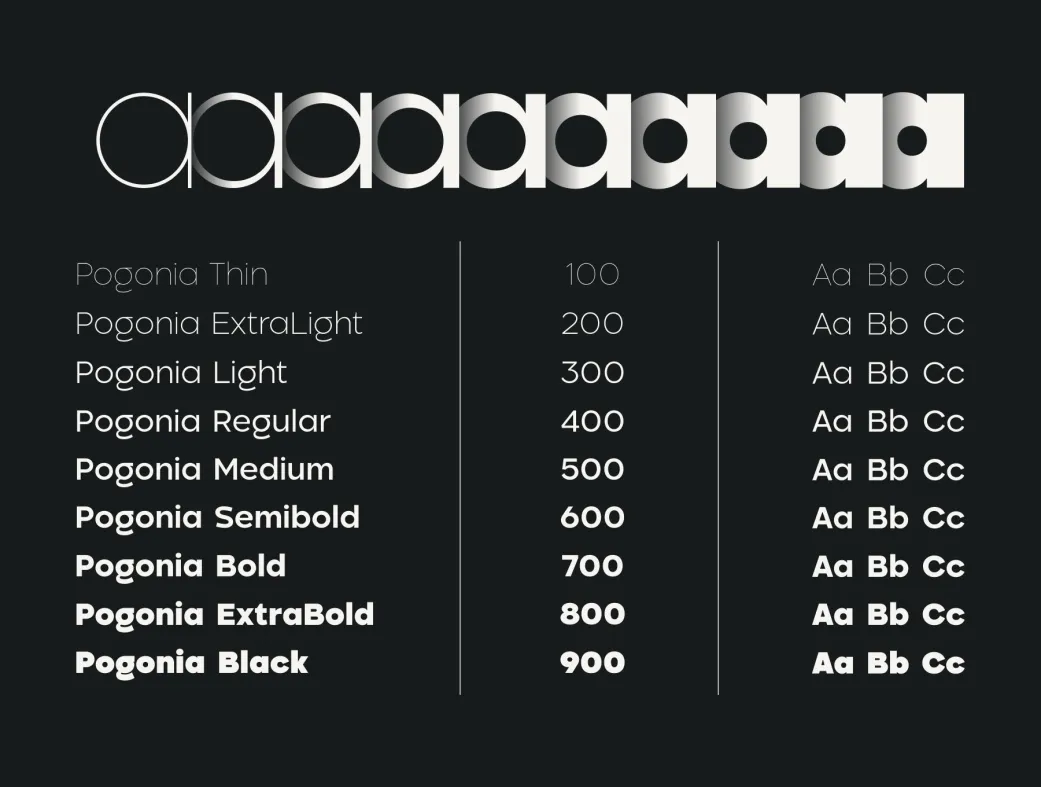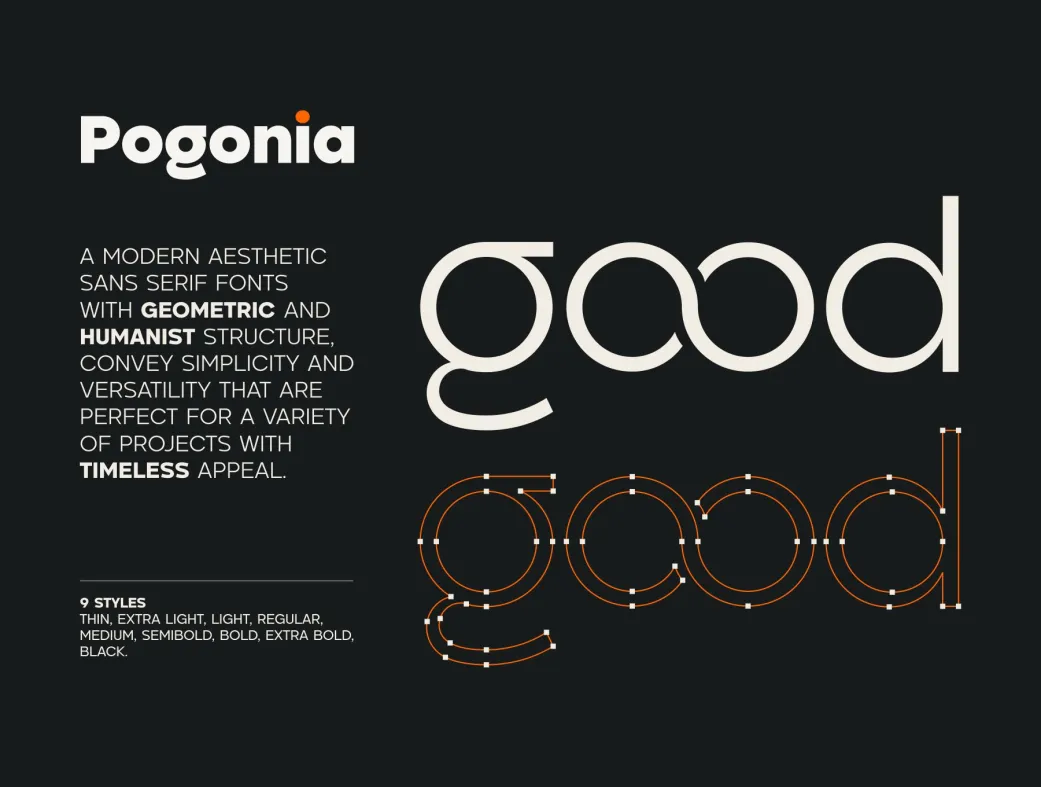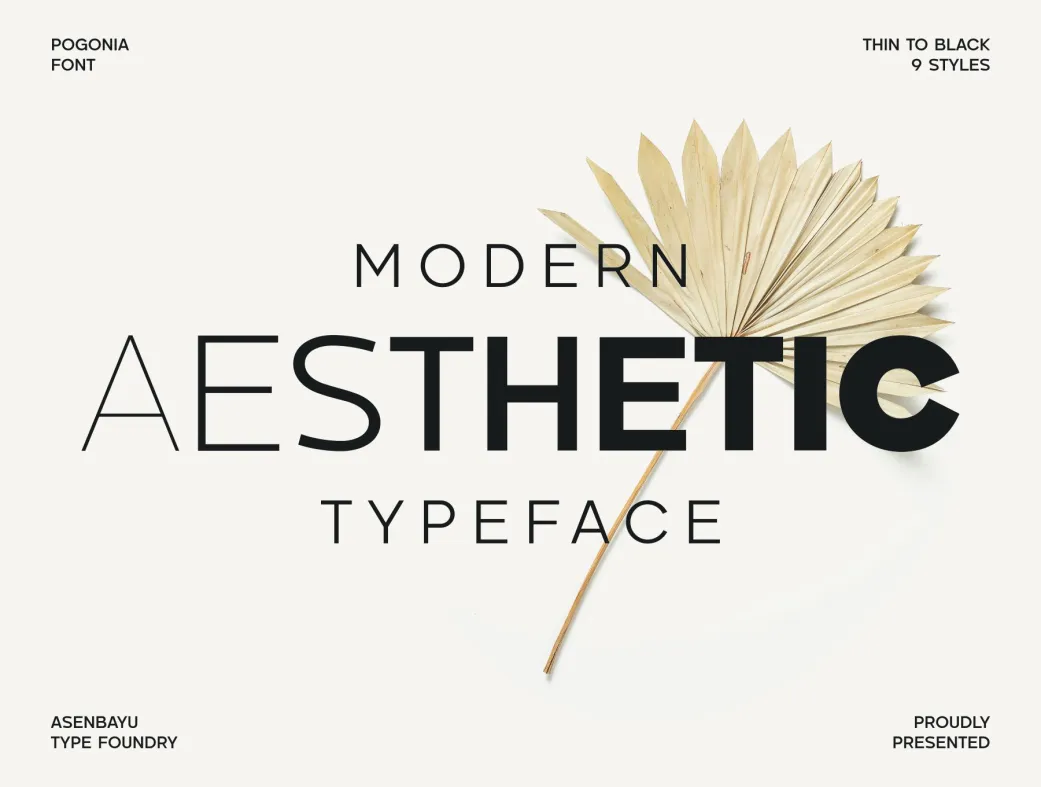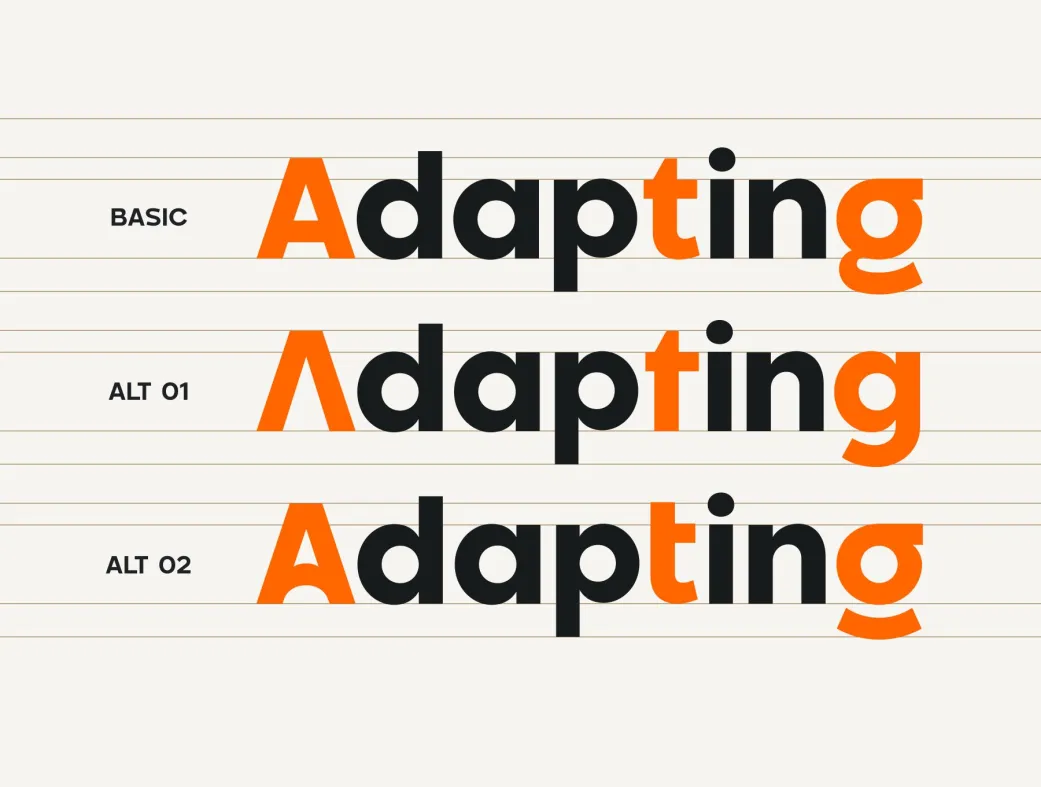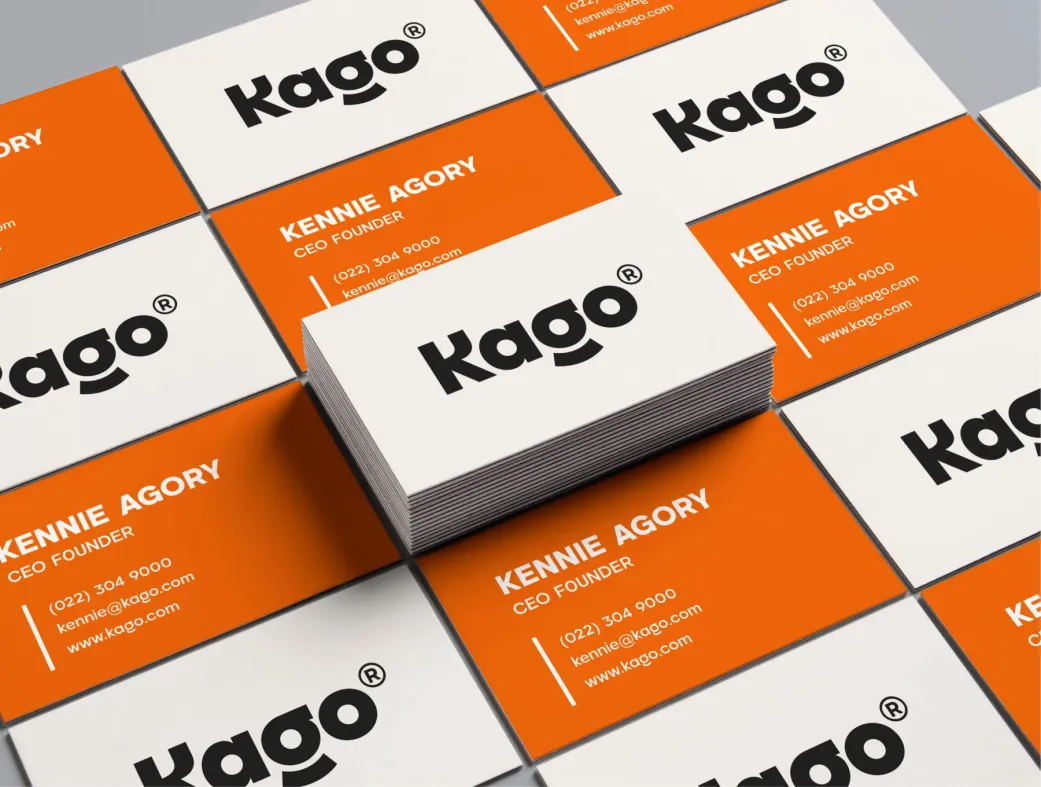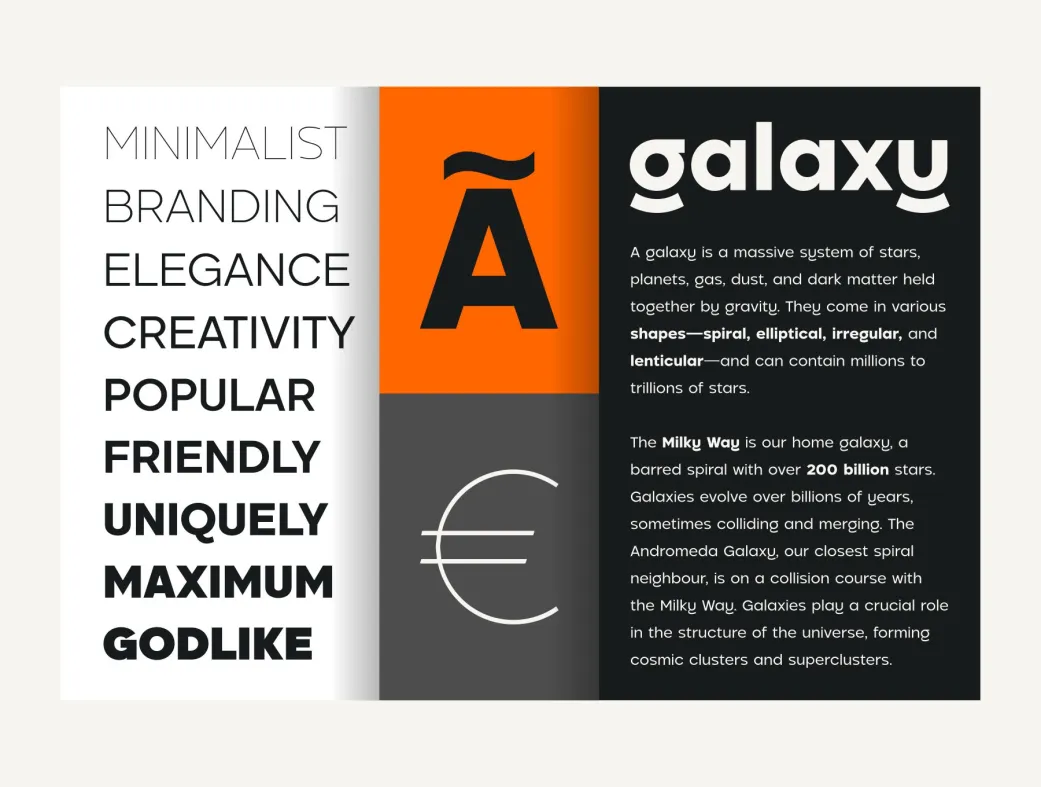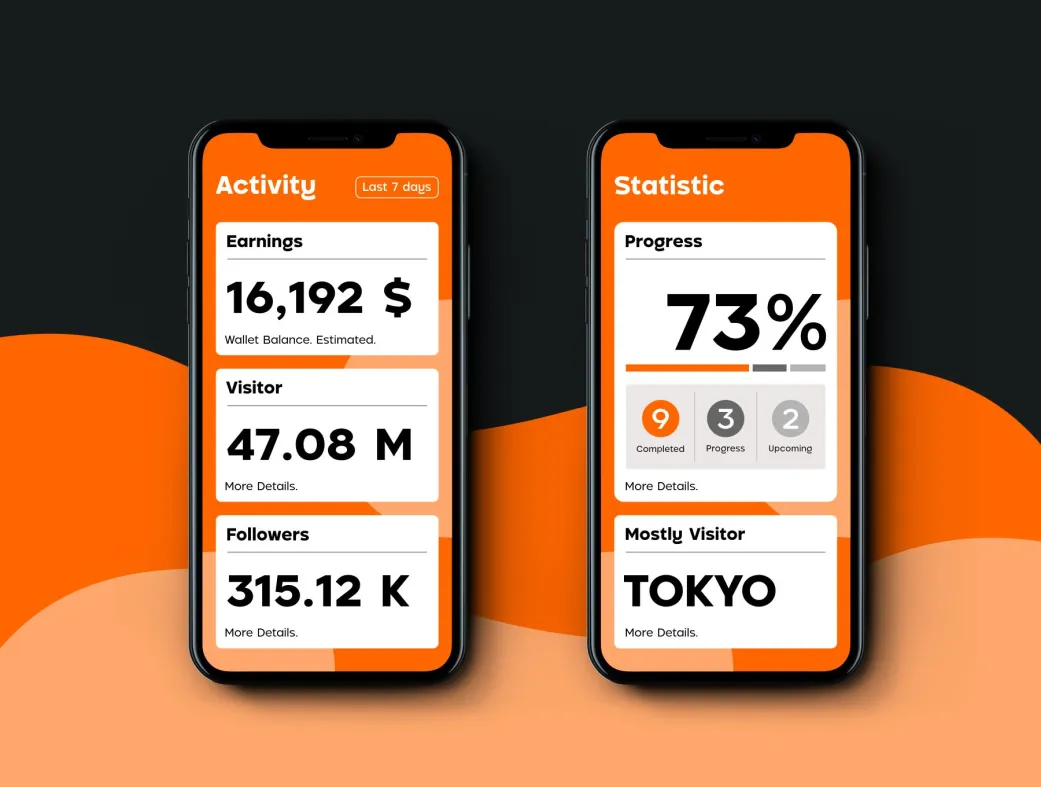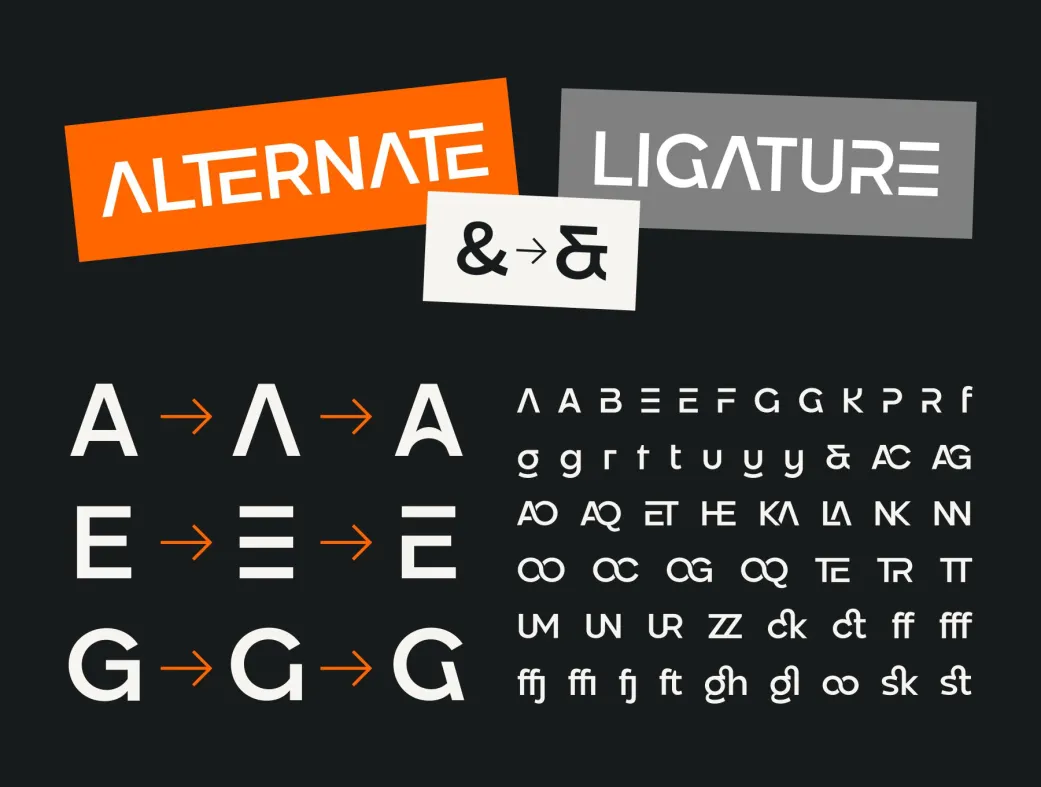
خانواده فونت پوگونی | Pogonia
فونت پوگونی با ۹ ضخامت و طراحی سنس سریف، انتخابی عالی برای پروژه‌های شماست!
Pogonia Font Family
خانواده فونت پوگونی | Pogonia | Pogonia Font Family
فونت پوگونی (Pogonia) یک خانواده فونت مدرن و زیبا با طراحی سنس سریف است که ساختار هندسی و انسان‌گرا را در خود جای داده است. این فونت با سادگی و تنوع خود، گزینه‌ای ایده‌آل برای پروژه‌های مختلف با جذابیت دائمی است. از این فونت می‌توانید برای طراحی لوگو، پوسترهای جذاب، طراحی‌های رسانه‌های اجتماعی، مد و وب‌سایت‌ها استفاده کنید.
فونت پوگونی شامل 9 نوع مختلف از ضخامت‌های نازک تا سیاه است که به شما این امکان را می‌دهد تا با توجه به نیاز پروژه‌تان، بهترین گزینه را انتخاب کنید. این فونت در سه فرمت OTF، TTF و WOFF ارائه می‌شود که به راحتی در نرم‌افزارهای مختلف قابل استفاده است. همچنین، حروف و نمادهای استاندارد، جایگزین‌های استایلیستی، لیگاتورهای استایلیستی، نمادها و نشانه‌ها، و پشتیبانی از چند زبان، از دیگر ویژگی‌های این فونت محسوب می‌شوند.
سادگی طراحی و قابلیت تطبیق‌پذیری این فونت، آن را به یک انتخاب عالی برای طراحان حرفه‌ای و مبتدی تبدیل کرده است. شما می‌توانید با استفاده از این فونت، هویت برند خود را به شکلی منحصر به فرد و جذاب ایجاد کنید.
• برای طراحان حرفه‌ای: با استفاده از جایگزین‌های استایلیستی و لیگاتورهای پوگونی، می‌توانید طراحی‌های منحصر به فردی را ایجاد کنید که توجه مشتریان را جلب کند.
• برای مبتدیان: با تنوع ضخامت‌های موجود، می‌توانید به راحتی از فونت پوگونی در پروژه‌های مختلف خود استفاده کنید و به سرعت به نتیجه دلخواه برسید.
2. چند نوع ضخامت در فونت پوگونی وجود دارد؟
فونت پوگونی شامل 9 نوع ضخامت مختلف از نازک تا سیاه است که می‌توانید بسته به نیاز خود انتخاب کنید.
3. آیا این فونت از چند زبان پشتیبانی می‌کند؟
بله، فونت پوگونی از چندین زبان پشتیبانی می‌کند و شما می‌توانید در طراحی‌های چند زبانه از آن استفاده کنید.